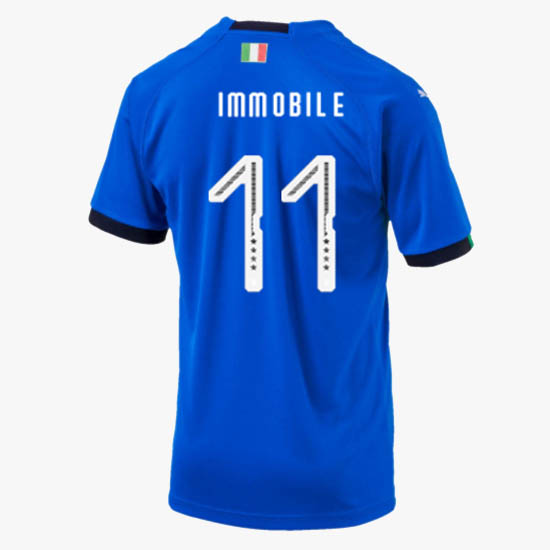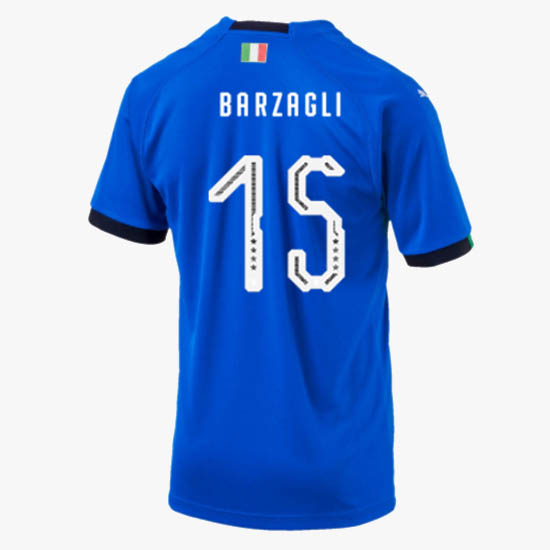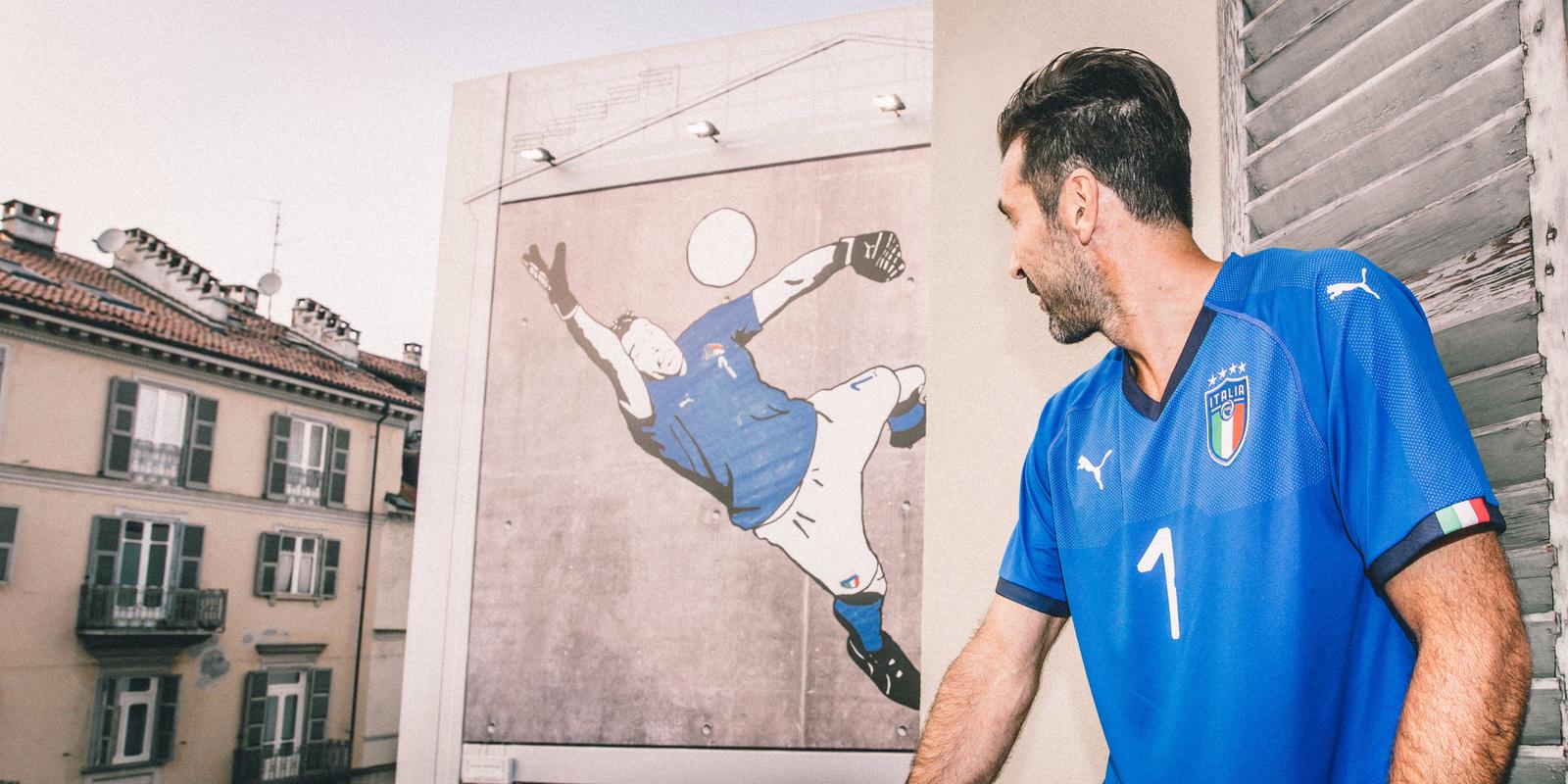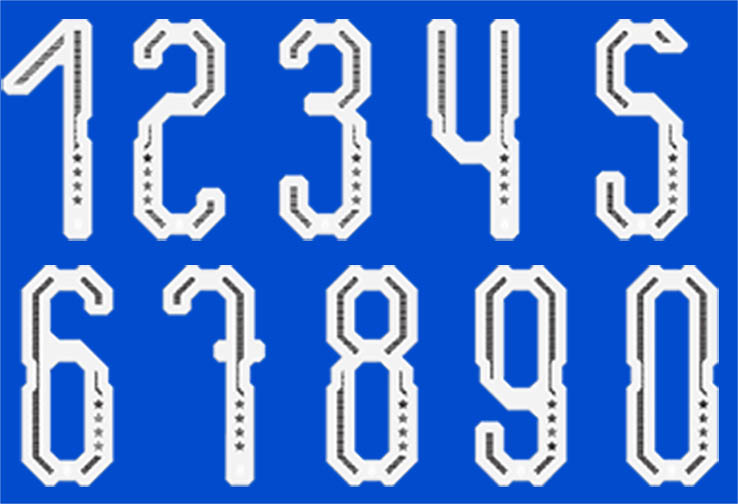
Einzigartige Puma Italien 2018 Schriftart enthüllt
Puma hat eine vollkommen neue Schriftart für das neue Italien 2018 Heimtrikot entworfen. Die neue Italien 2018 Schriftart zeichnet sich durch ein einzigartiges Design aus.
Puma Italien 2018 Schriftart
Hier sind einige Beispiele der neuen Italien-Schriftart auf dem brandneuen Heimtrikot.
Die neue Italien 2018 Schriftart, die eine einzigartige Form und Design hat, ragt aus normalen Schriftarten und Italiens eleganter 2016-Schriftart heraus. Jede Nummer der Italien 2018 Schriftart von Puma enthält Schnitte.
Interessanterweise enthält die Version der Italien 2018 Schriftart aus dem Verbandsstore vier Sterne und andere schwarze Elemente auf, während die Schriftart, die Buffon präsentiert hat, nur auf ein subtiles einfarbiges Italien-Wappen am unteren Ende setzt.
Es ist wahrscheinlich, dass andere Puma-Teams die gleiche Schriftartform wie Italien für ihre neuen Trikots und bei der WM 2018 verwenden werden, genauso wie es bei der EM 2016 der Fall war.
Italien EM 2016 Schriftart